Arthur Nelsons (1878–1957) faglige virke fra slutten av 1800-tallet fram til annen verdenskrig var svært allsidig, og gjør ham til en av de mest interessante boktrykkerne i norsk grafisk historie.
Etter min mening er han – ved siden av Hermann August Scheibler ved Fabritius (1854–1929) og Max Rich. Kirste ved Kirstes boktrykkeri (1873–1948) – den som i kraft i sitt faglige engasjement har betydd mest for norsk boktrykk.
Arthur Nelson gikk veien fra den såkalte «frie retning» på slutten av 1800-tallet til amerikansk klassisk typografi på begynnelsen av 1900-tallet. Tilbake i Norge arbeidet han for en klassisk retning i norsk typografi – i motsetning til en nasjonal stil, som mange ønsket. Deretter formidlet han prinsippene for den funksjonalistiske «nye typografien» i sitt eget fagtidsskrift.
Disse stilhistoriske brytningene er interessante for alle som er interessert i de grafiske fagenes fortid og nåtid.
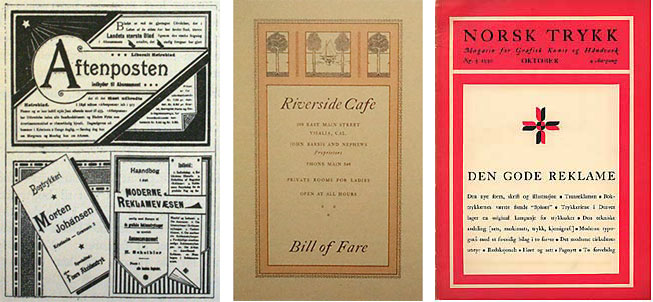
Tre grafiske produkter fra Arthur Nelsons hånd, som illustrerer hans faglige vei. Til venstre et konkurransebidrag fra 1897, i den «frie retnings» tid. I midten en meny han ga form til i 1912, mens han arbeidet i USA. TIl høyre omslaget til hans tidsskrift Norsk Trykk nr. 5 1930, der han argumenterte for den funksjonalistiske «nye typografien».
I denne artikkelserien – «Boktrykker Arthur Nelsons vei gjennom stilhistorien» – blir hele hans faglige virke klarlagt, med hovedvekt på hans rolle under «den nye typografiens» framvekst. Artikkelserien ble først publisert i Norsk Grafia, organ for Norsk Grafisk Forbund, i 2005.
For en kortere innføring i Arthur Nelsons rolle under modernismens framvekst i norsk boktrykk henvises til min tidligere artikkelserie «Den nye typografiens gjennombrudd i Norge 1–3». Denne artikkelserien var første gang boktrykkeren Arthur Nelson ble gjenstand for historisk oppmerksomhet.
ENGLISH SUMMARY
Arthur Nelson (born Nielsen) is one of the most influential Norwegian printers. His professional life began during the era of «artistic printing» during the 1890s. He then worked for 20 years in USA, where he met the revival of traditional typography, popular in parts of American graphical design. After returning to Norway in 1920 he was the first to argue for the modernist «new typography», which spread from the Soviet Union and Germany.
Et ungdomsbilde av Arthur Nelson, født Nielsen.